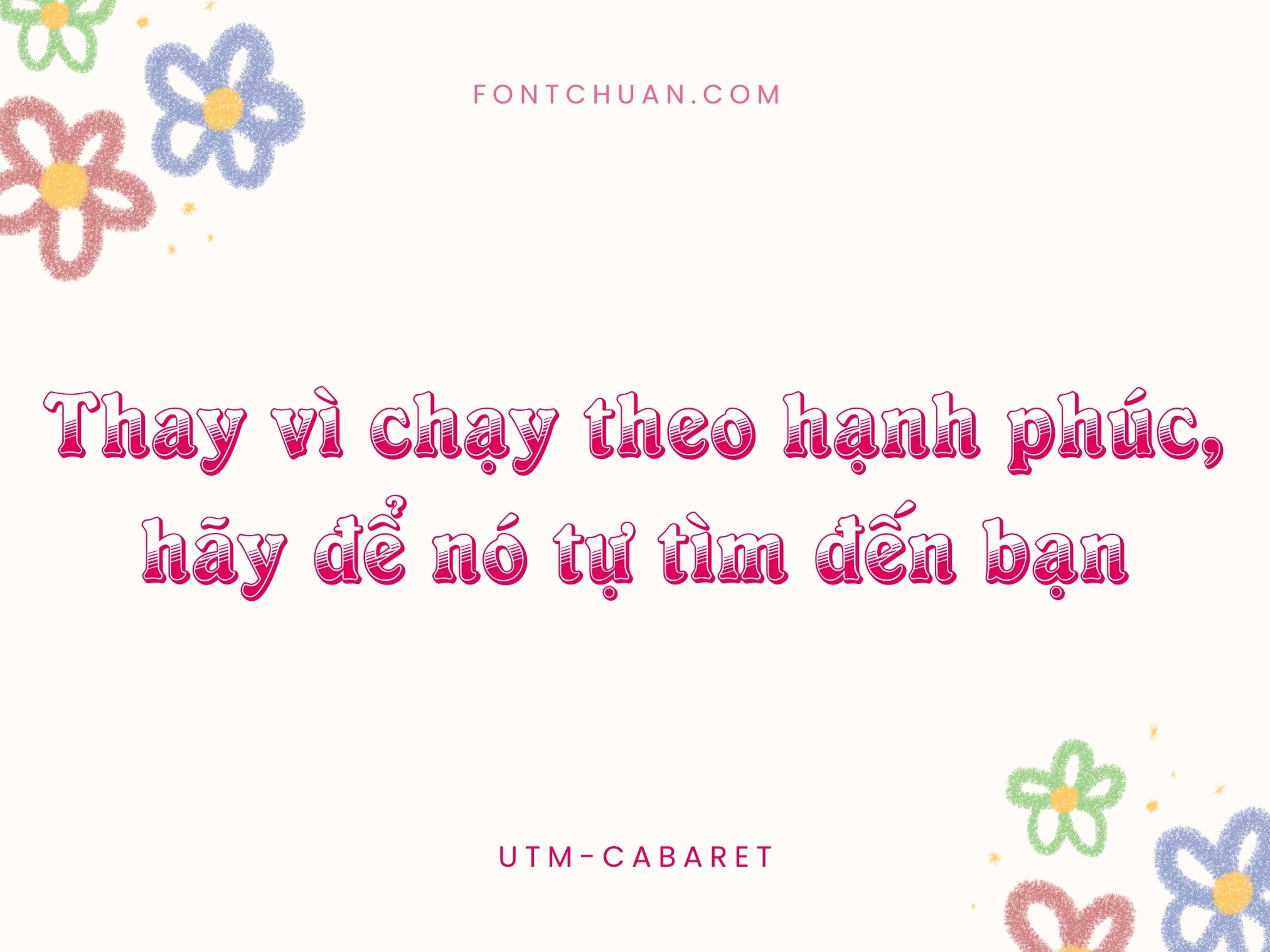
Font UTM Cabaret Việt Hóa
UTM Cabaret là phiên bản Việt hóa của font chữ Cabaret, một kiểu chữ decorative mang phong cách retro, gợi nhớ đến các biển hiệu và tiêu đề từ những năm đầu thế kỷ 20. Font này nổi bật với các ký tự in hoa, đường nét đậm và các chi tiết trang trí độc đáo, tạo cảm giác cổ điển và sang trọng. Phiên bản Việt hóa đã được thực hiện bởi Công ty TNHH Vitoen, hỗ trợ đầy đủ tiếng Việt cùng hơn 100 ngôn ngữ khác. Đây là một trong những font được cộng đồng thiết kế sưu tầm và chọn lọc nhằm đáp ứng nhu cầu đa dạng trong thiết kế.
UTM Cabaret có cấu trúc chữ với các nét đậm và chi tiết trang trí tinh xảo, tạo nên sự nổi bật và thu hút. Font này phù hợp cho các ứng dụng như thiết kế tiêu đề, logo, biển hiệu, áp phích và các ấn phẩm in ấn yêu cầu sự cổ điển và nghệ thuật. Các ngành nghề như quảng cáo, giáo dục, công nghệ và bất động sản có thể tận dụng UTM Cabaret để tạo điểm nhấn độc đáo trong thiết kế.